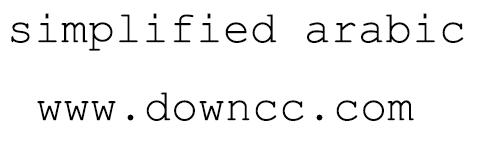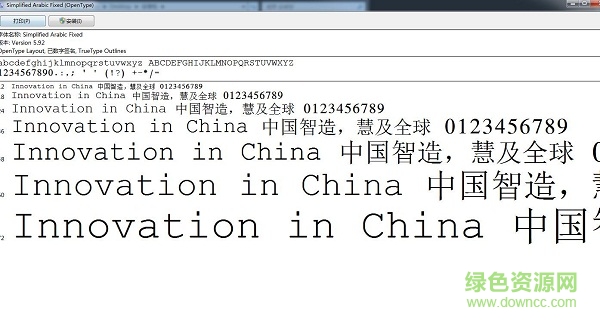
simplified arabic fixed
simplified arabic fixed字體是一款英文襯線字體,橫直均勻,結(jié)構(gòu)精準(zhǔn),工整規(guī)范,常用于內(nèi)文正文、網(wǎng)頁(yè)設(shè)計(jì)、ppt排版等方面,有興趣的朋友快來下載吧!
字體特征介紹
【字重】
字重大壁畫粗的字,自然會(huì)給人一種有力,厚重的感覺;
反之,字重小筆畫細(xì)的字,會(huì)給人一種纖細(xì),秀氣的感覺。
simplified arabic fixed
【負(fù)空間】
負(fù)空間小,字給人力量感,沉重感;
負(fù)空間大給人輕盈感,明快感!